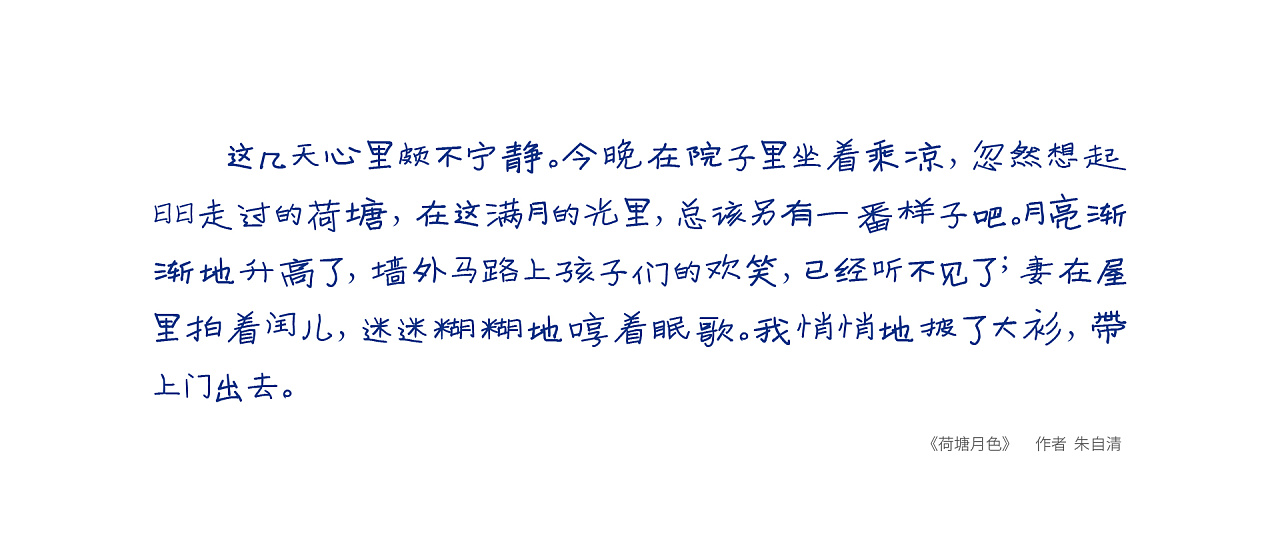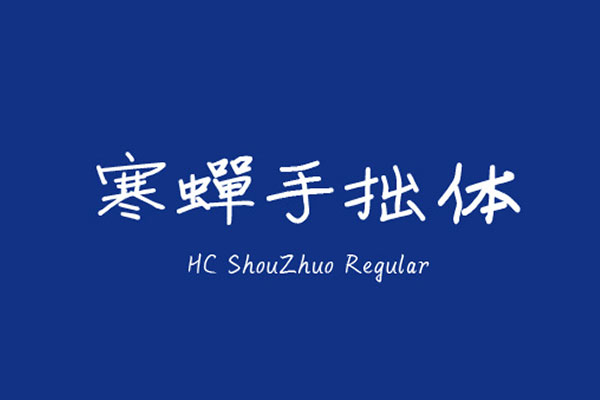
寒蝉手拙体
深圳设计师Siue精心打造了一款名为寒蝉手拙体的独特字体,这款字体的核心精髓在于发掘手写字体的自然之美,它给人们带来了逼真的手写视觉体验。尽管其应用范围有限,但寒蝉手拙体具有不可替代的独特价值。这套字体以独特的笔意和结构为基础,展现出一种与众不同的风格。
无论是制作海报、设计标志,还是进行其他类型的创意设计,寒蝉手拙体都是一个非常值得推荐的选择。它的手写风格给人一种亲切自然的感觉,可以为设计作品增添独特的魅力和个性。
寒蝉手拙体效果预览